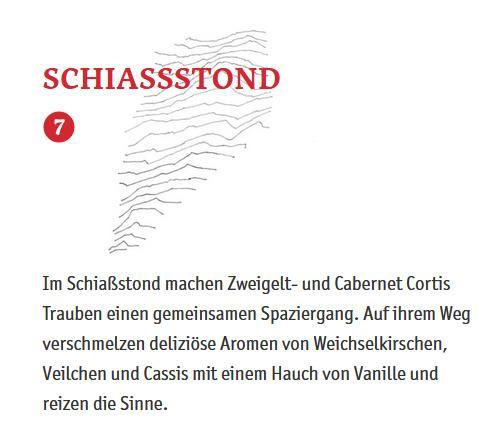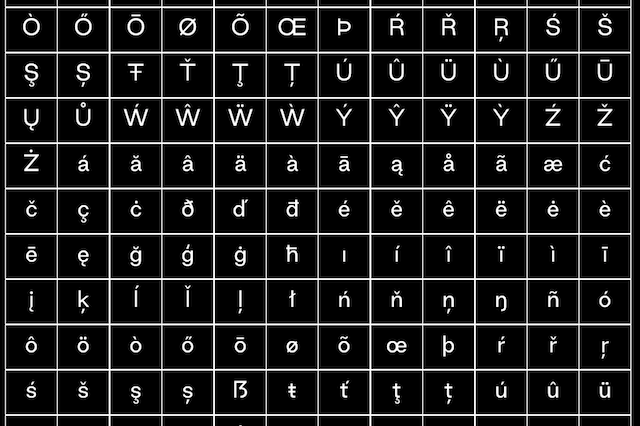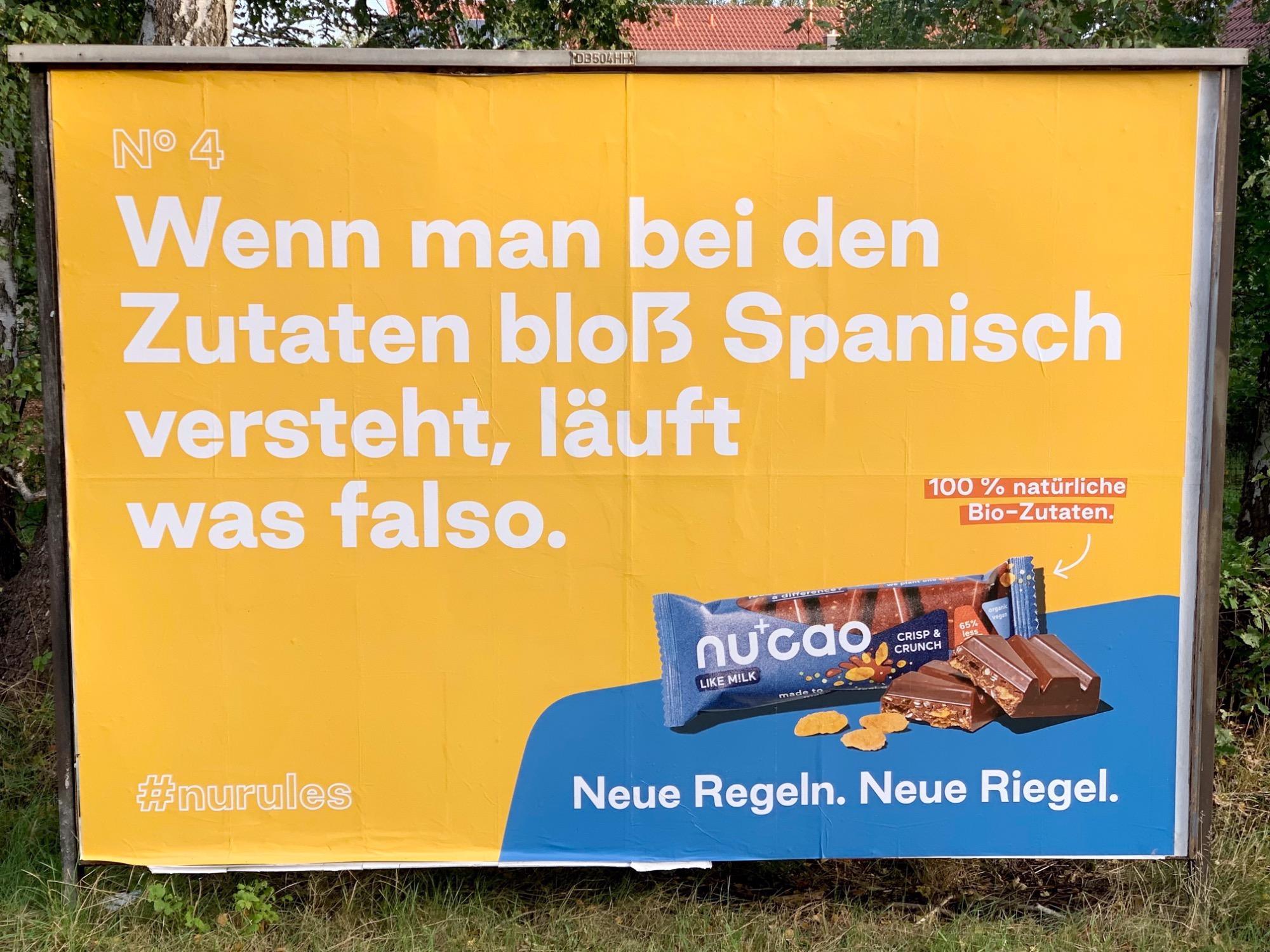
Dabei hätte ein echtes Versal-Eszett auf einem so aufgeräumten Weinetikett eine großartige Wirkung.
Hier hat man es beherzigt:
Auf der Homepage des Weingutes hat es noch nicht ganz geklappt. Ich habe echt Probleme, das Wort zu lesen, zumal ich es noch nie gehört hatte.
Soll das „Schießstand“ auf südtirolerisch sein? 🤷🏼‍♂️
Auf die Idee war ich nicht gekommen. Ich hatte beim Text darunter einen zweiten Hänger und las zunächst "diözese Aromen". Und dacht nur: "Oh Gott, die werden doch keinen katholischen Klerikalmuff in Flaschen packen". 😂
Ja, da könnte tatsächlich ein Konzept dahinter stehen und gleichzeitig drängt sich mir doch auch der Eindruck auf, dass das ẞ in dieser Schrift mit dem ß verwechselt wurde. Hier erfährt man mehr zur Kampagne und sieht das ẞ quasi in allen Texten falsch eingesetzt: